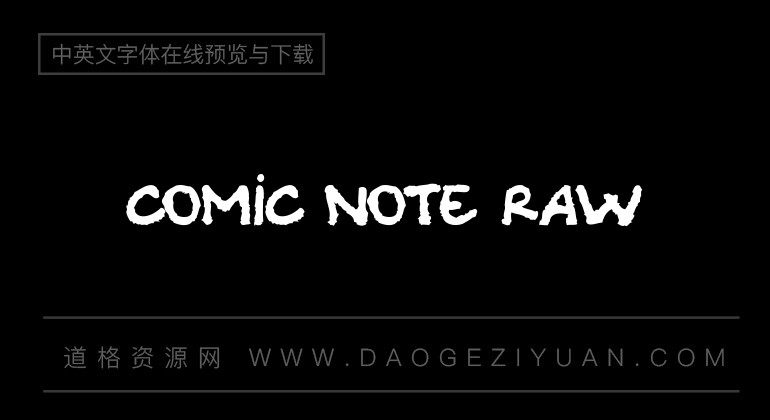
Comic Note Raw 是一款漫画风格的字体,它具有粗犷、粗糙的外观,搭配出现在的漫画风格很有感觉。它的字体特点是拥有较大的空白,字母的外观看起来很有层次感,可以更好的表达漫画的情绪。它还具有良好的可读性,可以使漫画的文字更加清晰,更容易被读者理解。内容介绍
Comic Note Raw是一款非常不错的手写艺术字体,具有很好的视觉感,适合于文化类的宣传设计、商业类品牌的广告和产品包装设计以及个性化文字排版等较多场景。